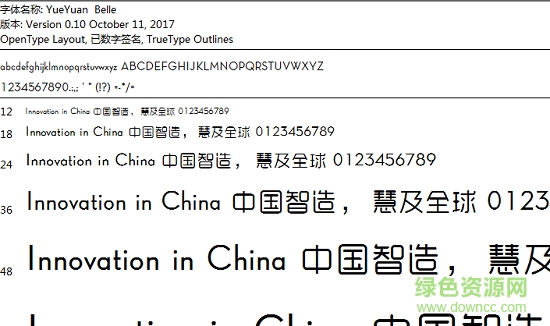
悅思體ttf是專為需要這款字體的朋友準(zhǔn)備的,這款字體對(duì)有些筆畫進(jìn)行了圓角處理,這樣會(huì)讓這款字的機(jī)構(gòu)顯得非常的緊湊,歡迎下載使用!
悅思體ttf是一款字形工整簡(jiǎn)潔的中文字體,這款字體的整體效果出眾,整體看上起在嚴(yán)肅中又帶著幾分俏皮,非常適合用作設(shè)計(jì)方面!